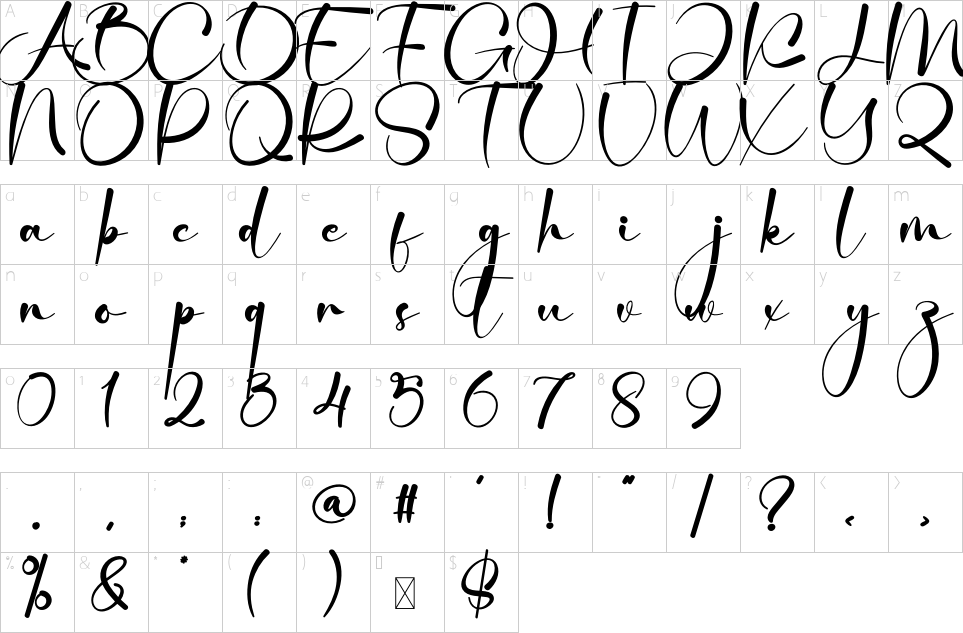
Dancer Christmas Font
Aqui está uma breve descrição para a página de download da fonte ‘Dancer Christmas Font’, adequada às instruções: Descubra o espírito natalino com Dancer Christmas, uma fonte criada especialmente para você manter o clima festivo em seu trabalho. Designada por scratchones, esta elegante fonte adquire um toque de diversão e alegria durante as férias de Natal. Dancer Christmas é perfeitamente adaptável para aplicativos gráficos natalinos ou até mesmo para criações decorativas que exibem uma pitada de festa. Seja em seu trabalho, projeto pessoal ou mesmo em criações de sites e redes sociais, esta fonte adicionará um toque especial e único. Com a facilidade do download gratuito disponível tanto para Windows quanto para Mac, você pode começar a usar Dancer Christmas agora mesmo. Escolha entre sua versão padrão e variante negra para garantir que seu trabalho tenha uma aparência impecável durante o Natal. Com certeza, ela será um excelente aditivo ao seu próximo projeto criativo ou de design natalino.
Mapa de caracteres da fonte Dancer Christmas Font